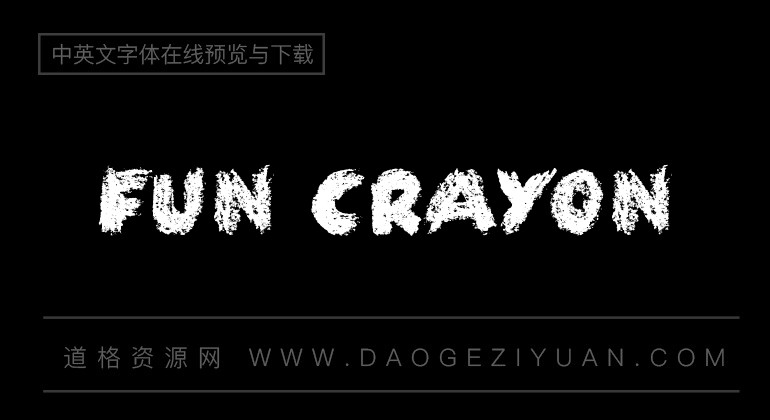
Fun Crayon
Fun Crayon是一款充满活力的字体,它有许多活泼的颜色和形状,可以让你的文字变得更加有趣。它的字体风格易于阅读,适合用于孩子们的学习和娱乐。它可以用于创建各种有趣的设计,包括卡片,海报,书籍封面等等。它的简单易懂的字体风格可以让您的文字更加生动有趣。
Fun Crayon是一款非常不错的手写艺术字体,具有很好的视觉感,适合于文化类的宣传设计、商业类品牌的广告和产品包装设计以及个性化文字排版等较多场景。